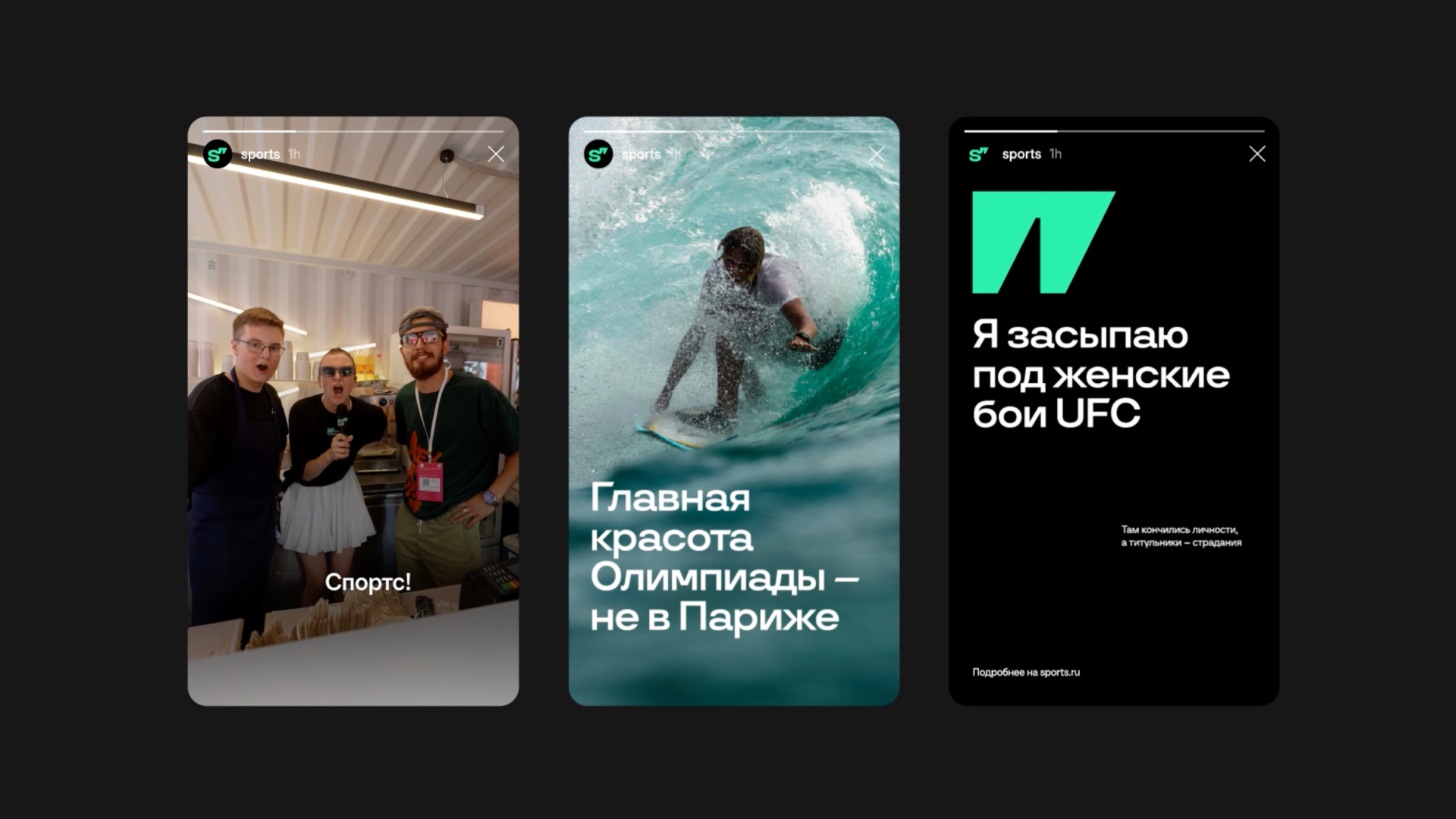
Заказной шрифт
Sports"
Новый образ главного спортивного медиа страны – яркий, смелый, диджитальный. Миссия бренда заключается в простой фразе – «Делаем спорт лучше», а суть – «Все измерения спорта. Ищем. Создаем. Показываем». Sports.ru – это только доменное имя в адресной строке. Название бренда – просто Sports или кириллическое Спортс. Теперь это равноправные варианты написания.
Новый логотип имеет важные для болельщиков смыслы: во-первых, это международно признанный знак на секундомерах и табло, а во-вторых – время вечный спутник великих моментов в спорте. Воспоминания превращаются в истории, которые мы хотим пересказывать друзьям и близким. Истории, которые красиво рассказаны на Спортсе, и которые хочется перечитывать даже спустя годы, заключены в кавычки. Они символизируют то, как Sports рассказывает о событиях спорта – цитатами, прямой речью зрителей и участников.
Для акцидентных заголовков был разработан фирменный шрифт TT Sports. Скосы в геометрии знаков повторяют угол наклона фирменных «секунд-кавычек» и добавляют в шрифт динамику. Шрифтовой набор TT Sports содержит не только альтернативные глифы и специальные символы, но и кириллическую и латинскую версии логотипа, которые можно добавлять в наборный текст с клавиатуры.
У бренда появился основной фирменный цвет, которого никогда в истории у логотипа Sports не было. Мятно-зеленый цвет становится одним из инструментов идентификации, а для медиа это особо важный инструмент в коммуникации.
Фирменные паттерны могут быть статичными и динамичными. Они используются в различных вариантах масштаба. Для разделов сайта были разработаны чистые и лаконичные пиктограммы, которые эффектно смотрятся в диджитал-среде, особенно в малых размерах на цифровых экранах.
В качестве PR-кампании ребрендинга на улицах Москвы появились сотни плакатов с временем и цитатами, которые изменили мир. Они были расклеены по городу без упоминания самого бренда Sports, фото с ними выложили известные люди в мире спорта к себе в соцсети. А на футбольном матче на трибуне болельщики в дождевиках фирменного цвета сформировали знак Спортса.
Вместе с «Ничего обычного» обновленный Sports выпустил фирменный мерч: футбольное, хоккейное и бейсбольное джерси, худи, сет футболок, дождевик, и, разумеется, носки. Sports напоминает, что спорт в России — это всегда большое событие.